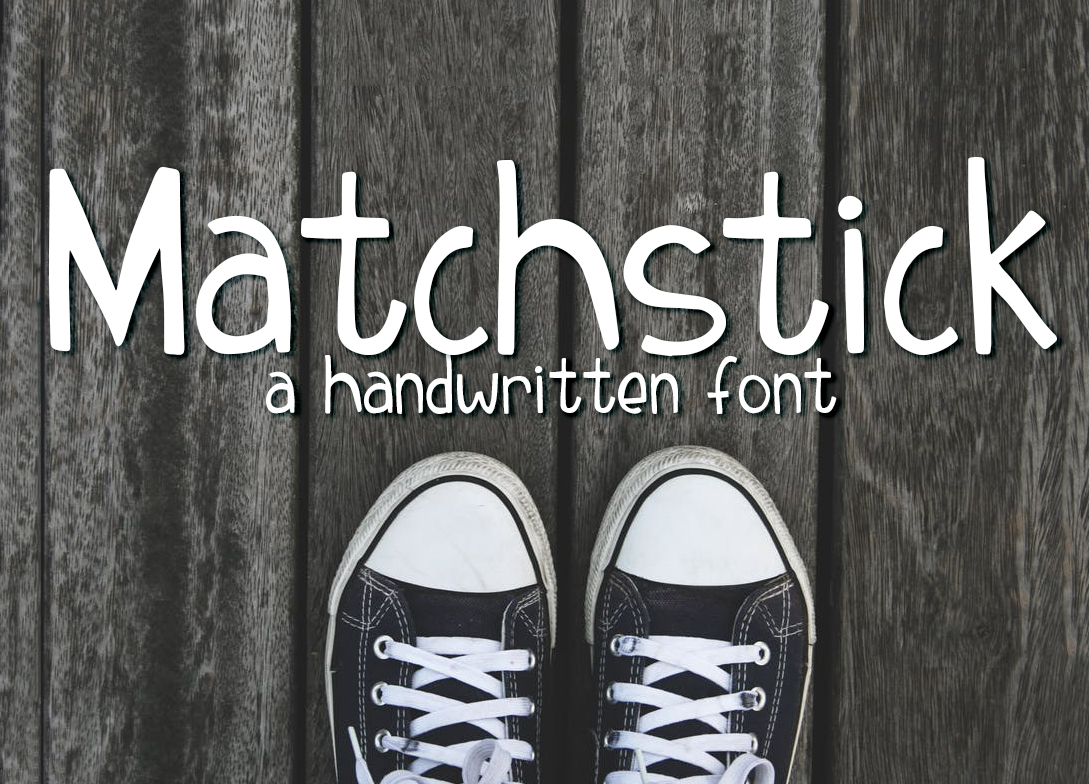
Matchstick Typeface – Download Grátis
Estou é uma oportunidade maravilhosa para apreciar a Matchstick Typeface, uma elegante fonte escrita à mão criada pelo designer Groovyjournal. Esta fonte transmite um encantamento autêntico e natural, perfeitamente adaptada para expressar textos em projetos de arte digital, design gráfico ou mesmo em elementos como nomes de empresas. Se você aprecia essa fonte, uma pequena contribuição de $1 é muito bem-vinda. Este apoio ajudará Groovyjournal a investir mais tempo no desenvolvimento e na criação de novas fontes, mantendo o seu trabalho único e inspirador à disposição para todos nós. Obrigado por apreciar Matchstick Typeface!